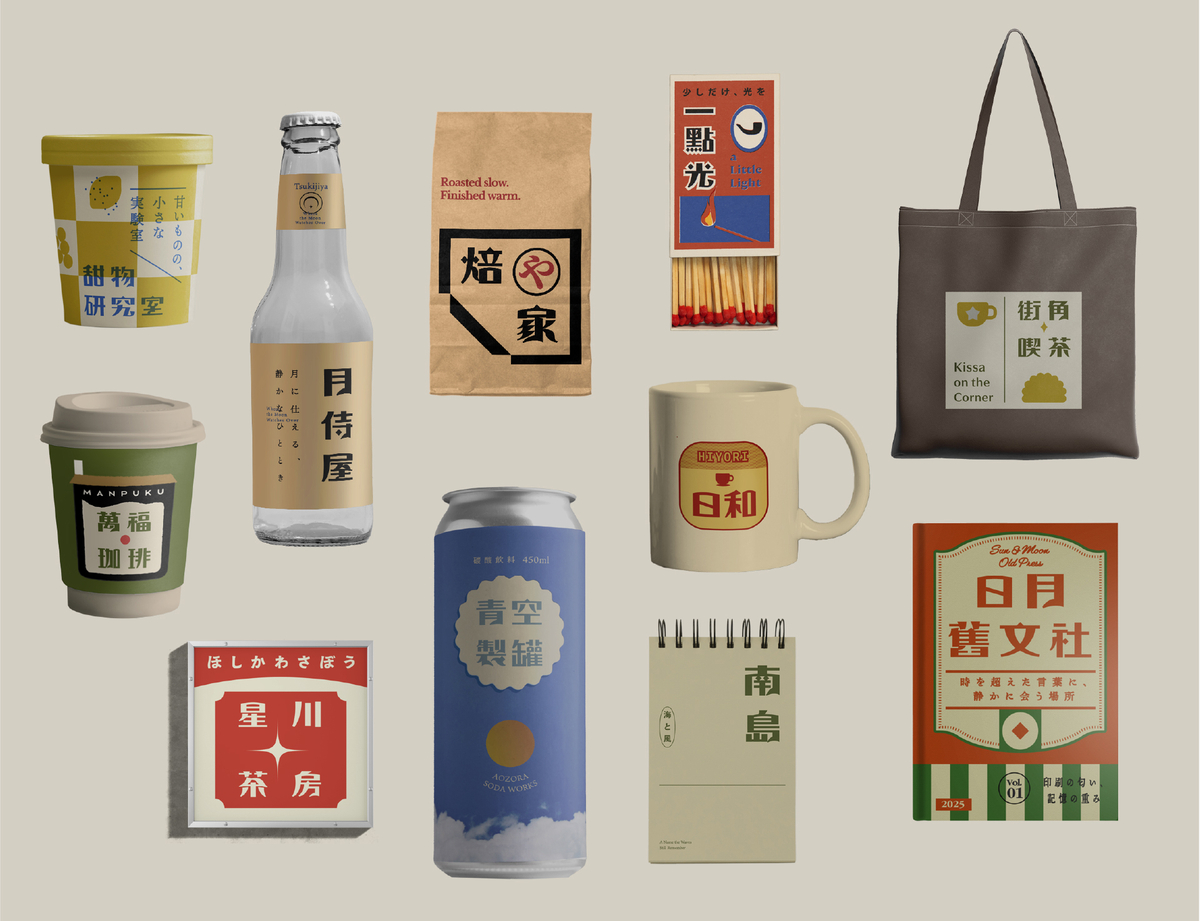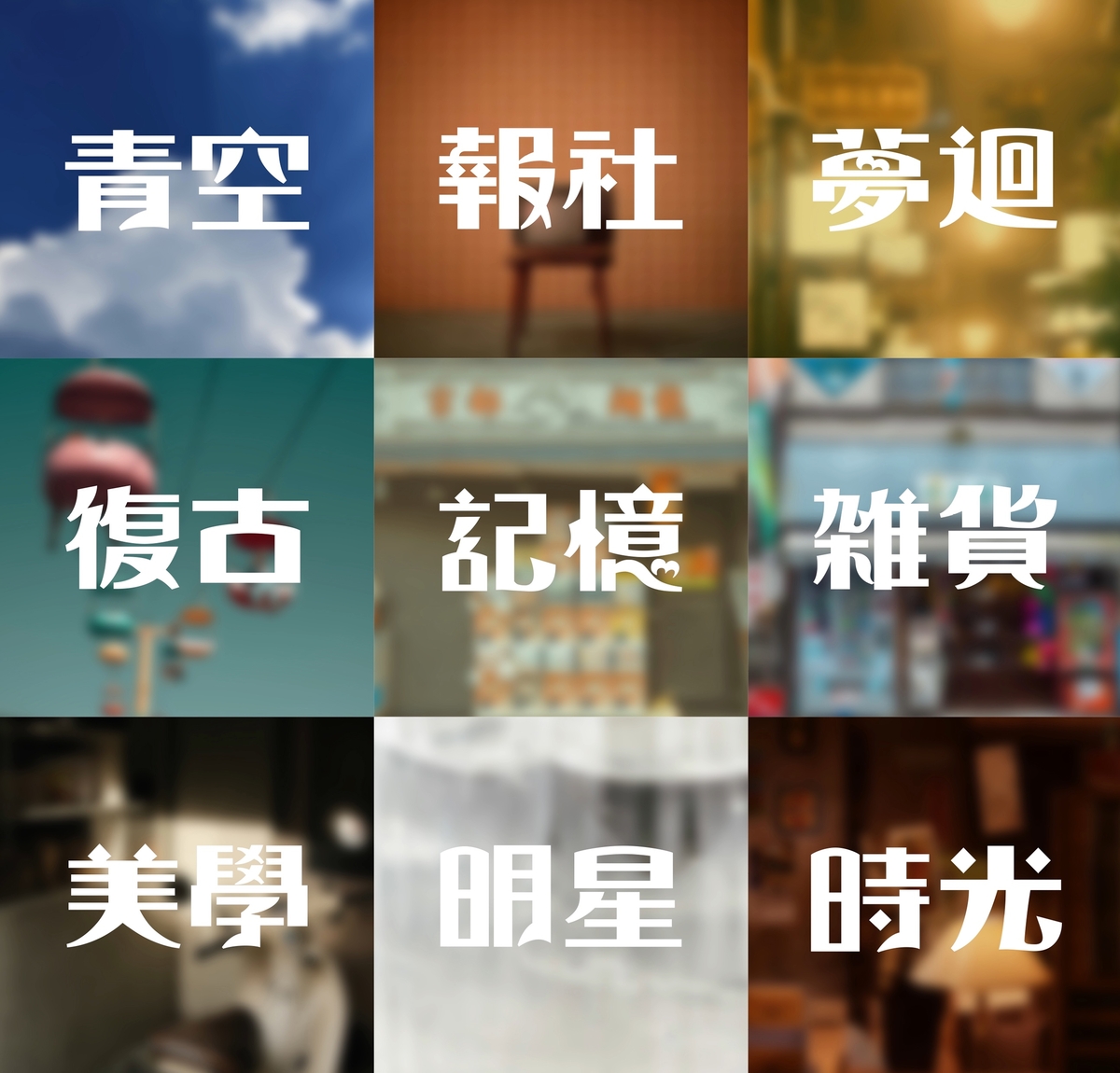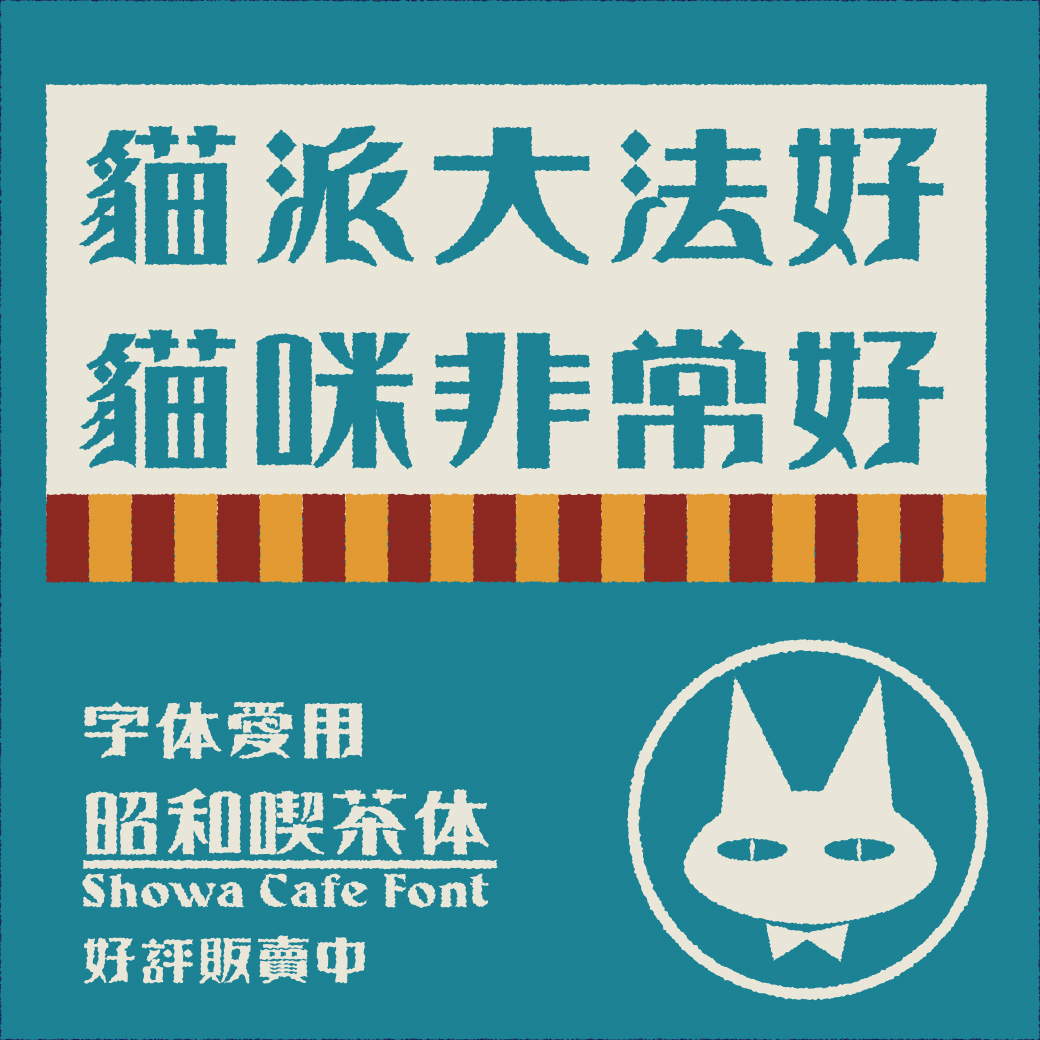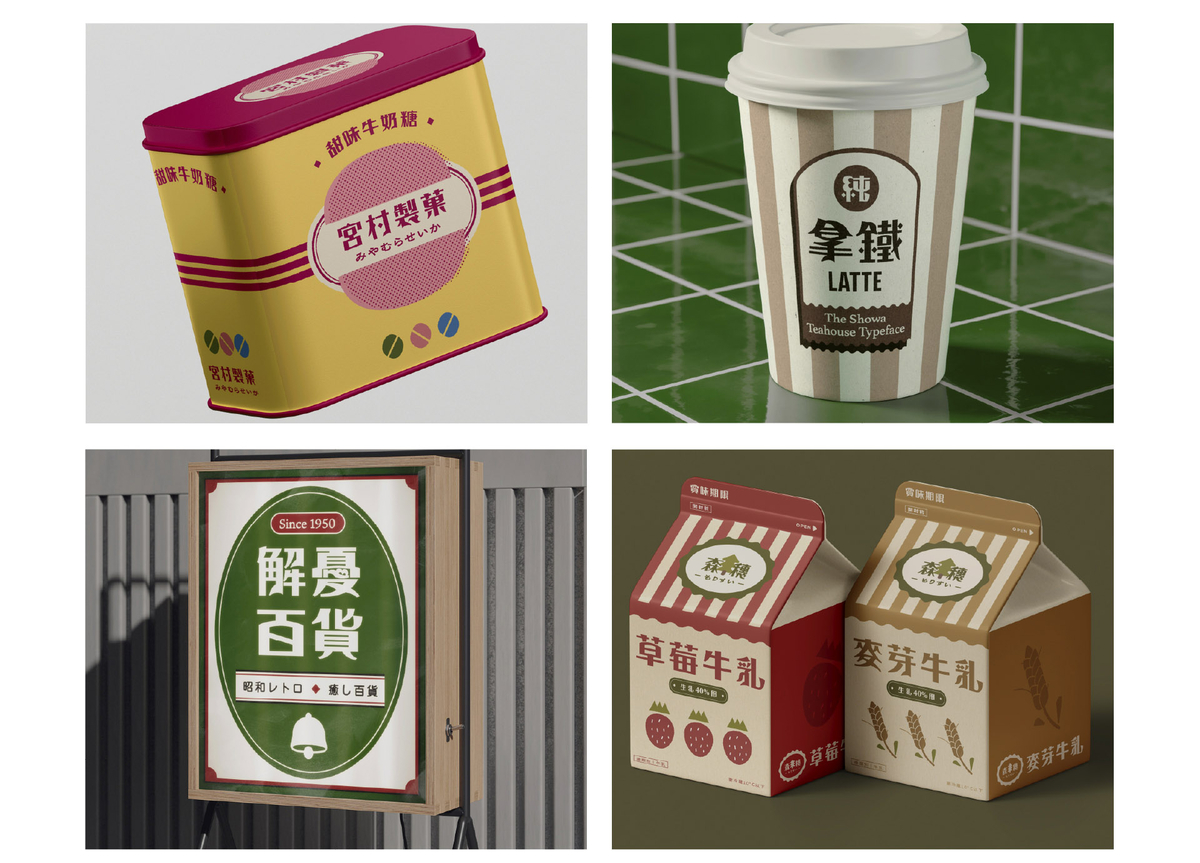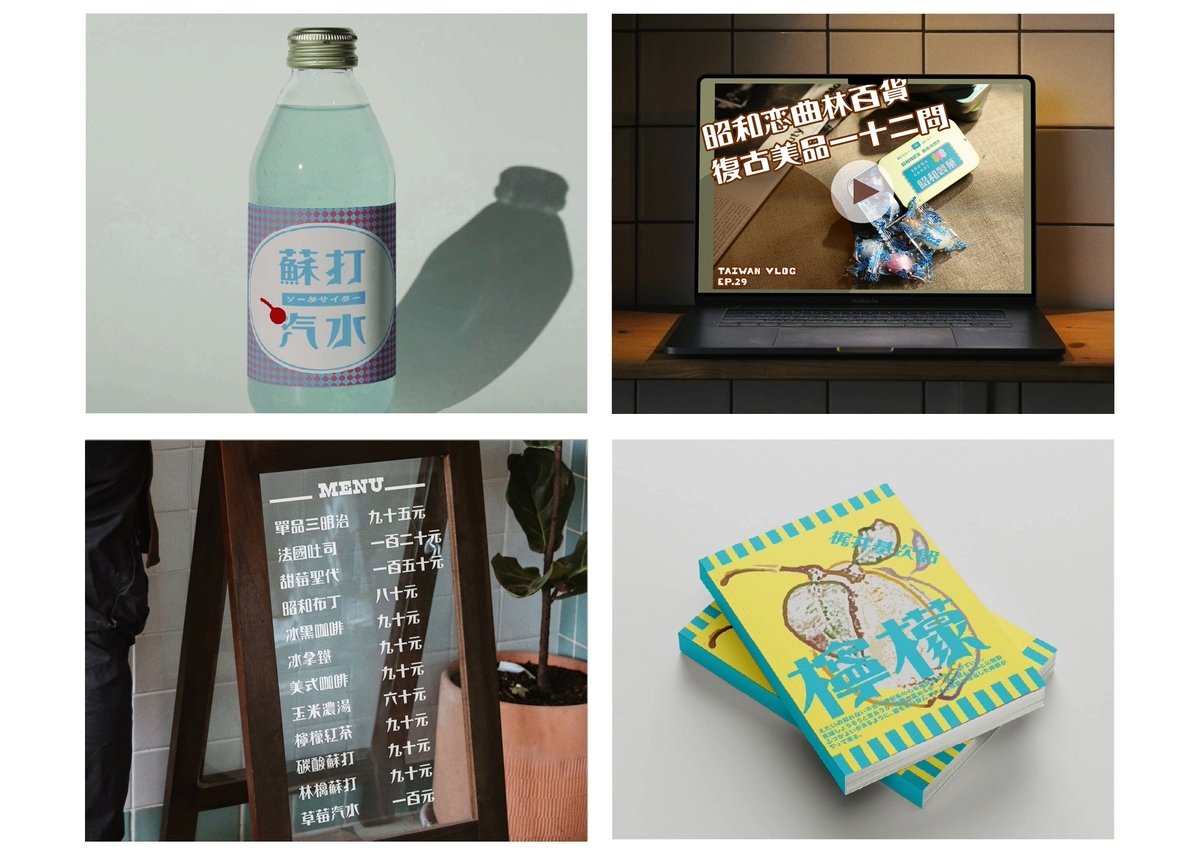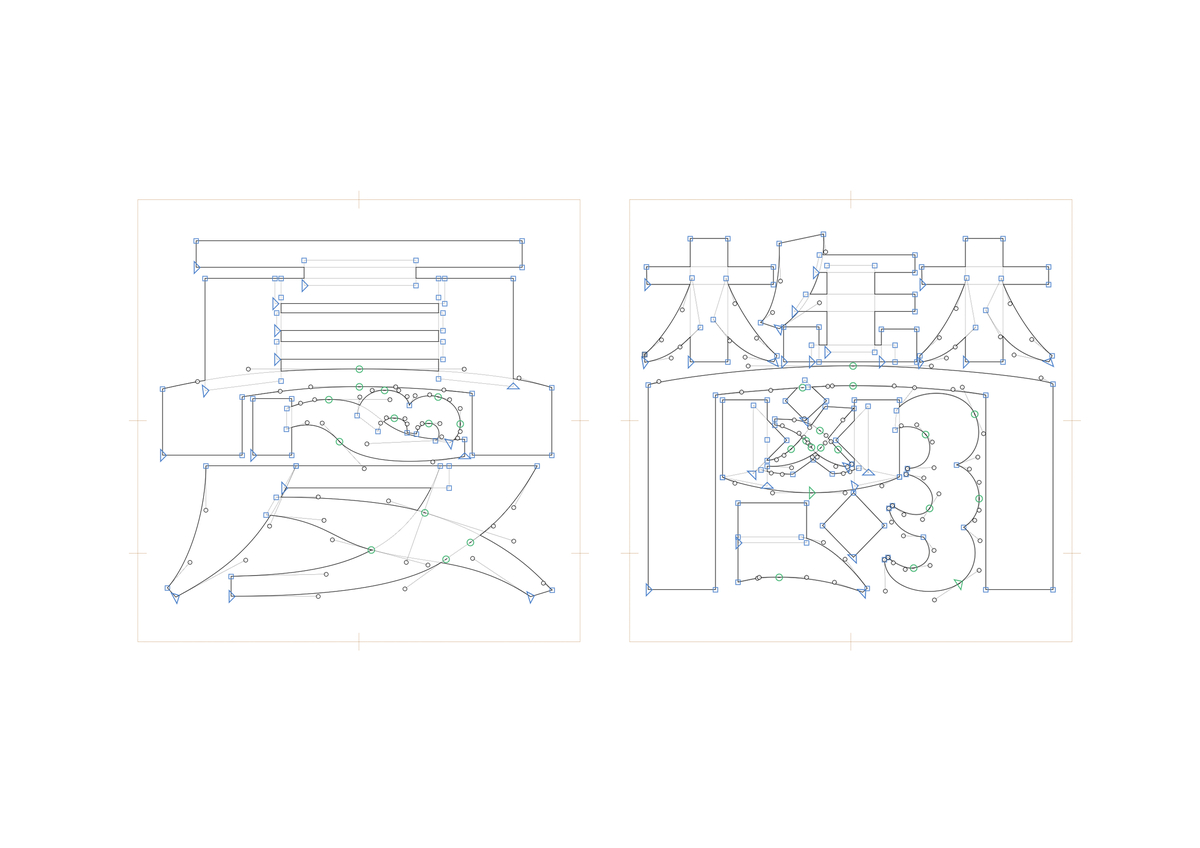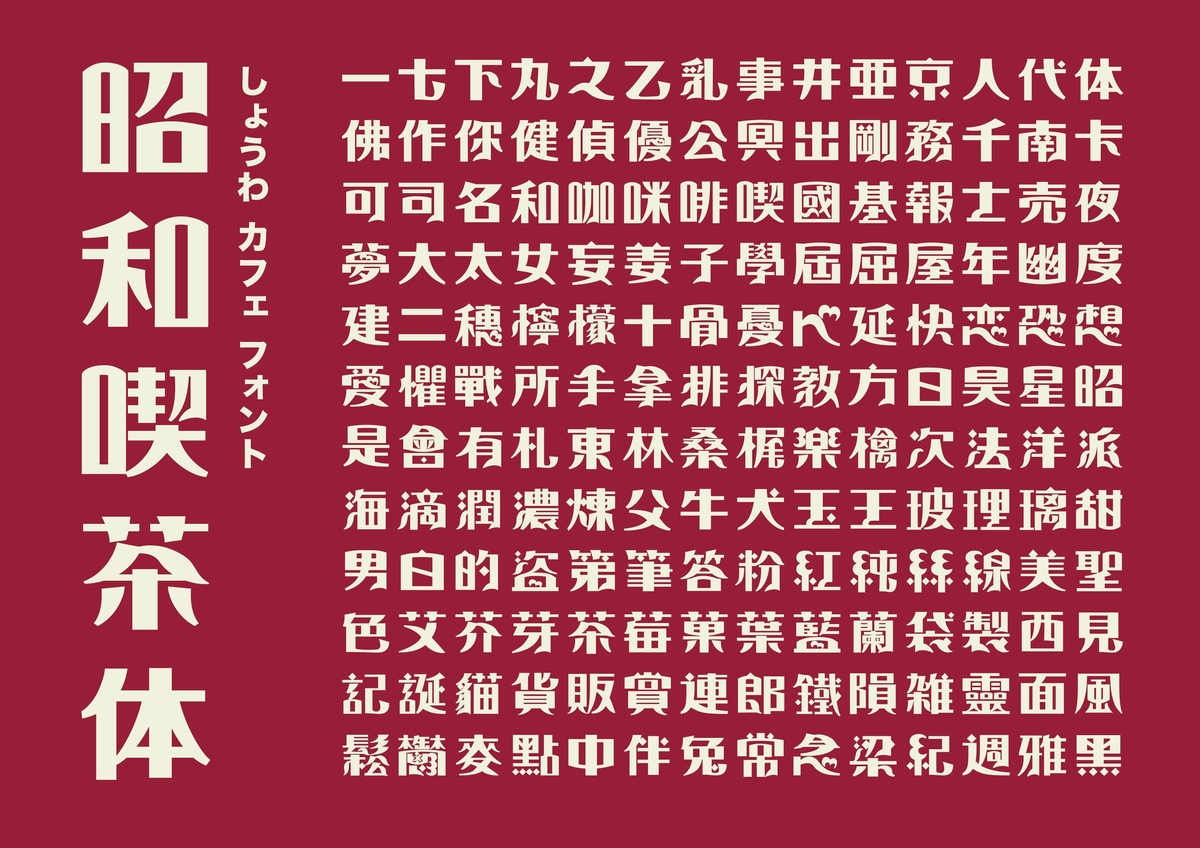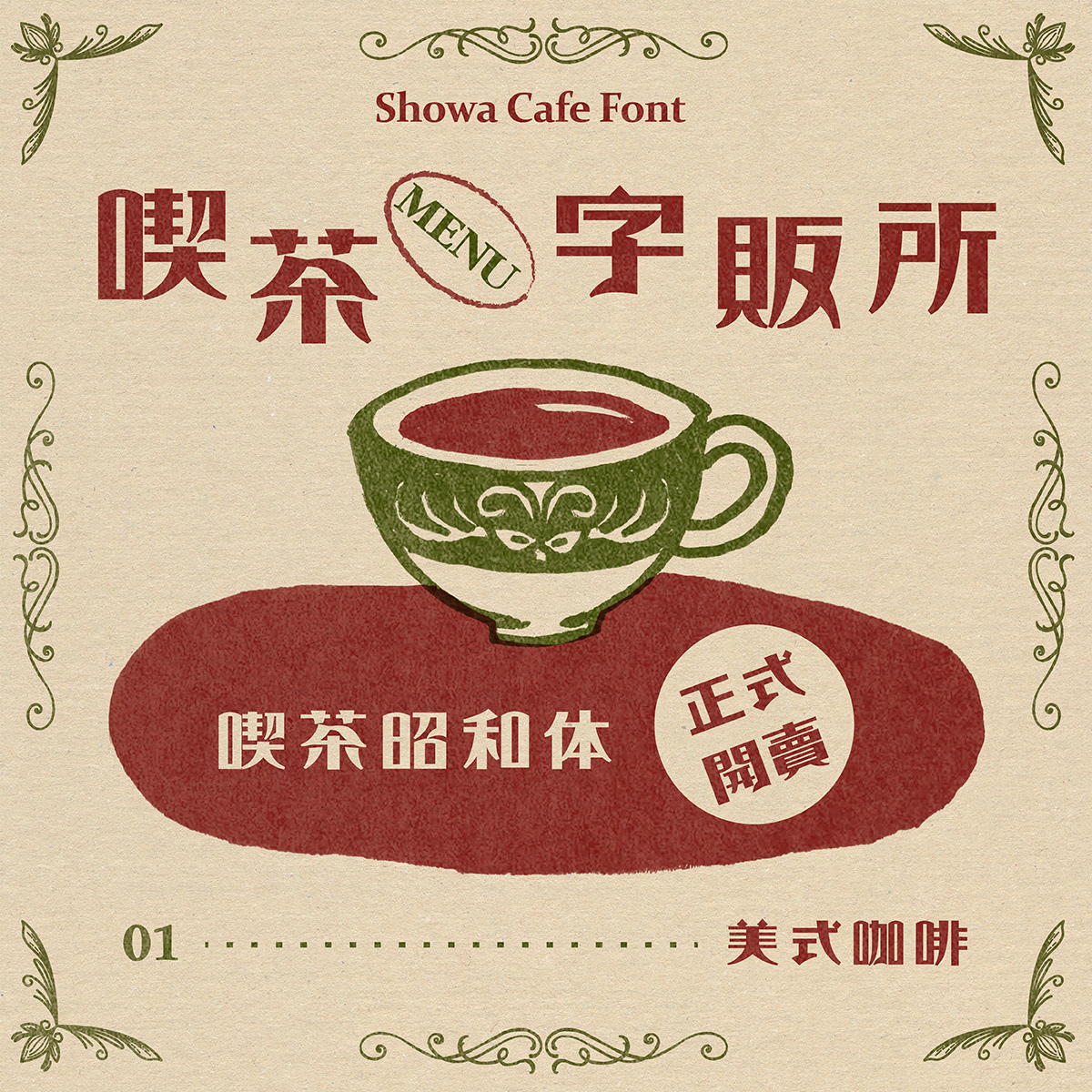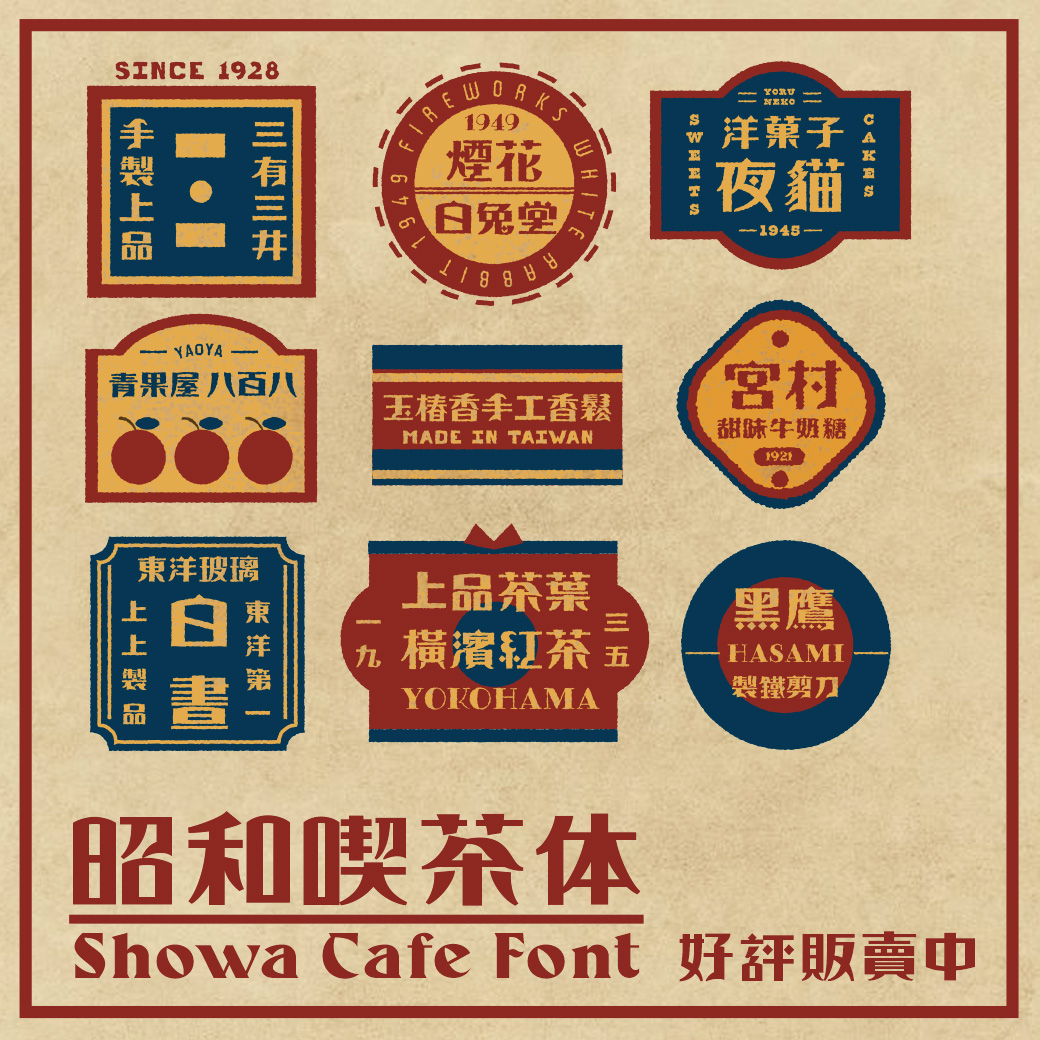
《昭和喫茶體》|【復古昭和●大正浪漫】沖一壺懷舊的咖啡,寫一首溫柔的詩句,讓我們一起浪漫的回到過去
一套以日本大正,昭和時期的復古美術字為基底,復刻再造的字體提案
『你也在尋找一款有特色的標題字體嗎?』
『是否在製作簡報時,總是選來選去就是那幾款字呢?』
『用心特地選了字體,但看起來好像沒有太大差別?』
別擔心 ! 這裡一款超具有特色的復古字體推薦給你
窄巷微光中,咖啡香緩緩漫出,玻璃門輕響,迎來黃昏的腳步。
老唱片轉啊轉,音符不急也不躁,螢光燈下的字,是那夜裡的溫柔。
玻璃木窗半敞,書頁間彼此安靜的對飲,褪色的磁磚間,只想與月光悄悄說故事。
在這片土地度過的歷史中,曾存於這小小的島嶼上一段時間。
祖父家客廳上的老報紙;雜貨店外那發出噪音的舊冰箱,
米舖牆上的斤兩價格表;冰菓室招牌下歡笑的年輕男女。
彼此在記憶中,若有似無的歷經過的昭和時光
歷史的痕跡,在筆劃中悄悄地輕聲細語著。
嘿,那會是我們共同的記憶嗎?
你是否在做設計或排版的時候,時常感覺到沒有適合的標題型字體?
常常換來換去,但好用的字體就只有那麼幾種 ?
在選擇字體時,在保守安全以及特色優點上時常難取得平衡
有沒有那麼一種字體,不僅辨識度高,同時又具有令人印象深刻的特色呢?
在時光緩步流轉的年代,帶著溫度與靜謐。
映著茶店的玻璃、飄過手沖咖啡的蒸氣、嚐口手工甜點的甜膩。
每一筆,每一劃,像是老匠人精心寫下的生活節奏,
緩緩地,不急不躁地,將你我帶入一段不被打擾的午後時光。#